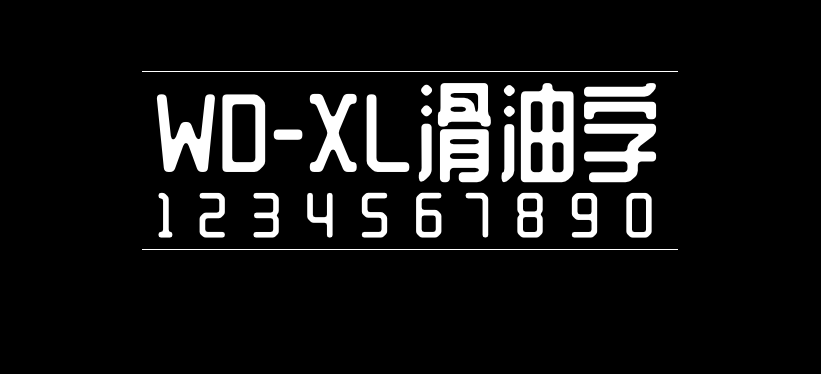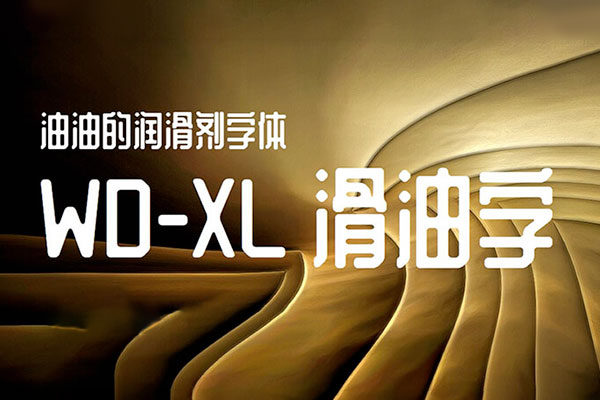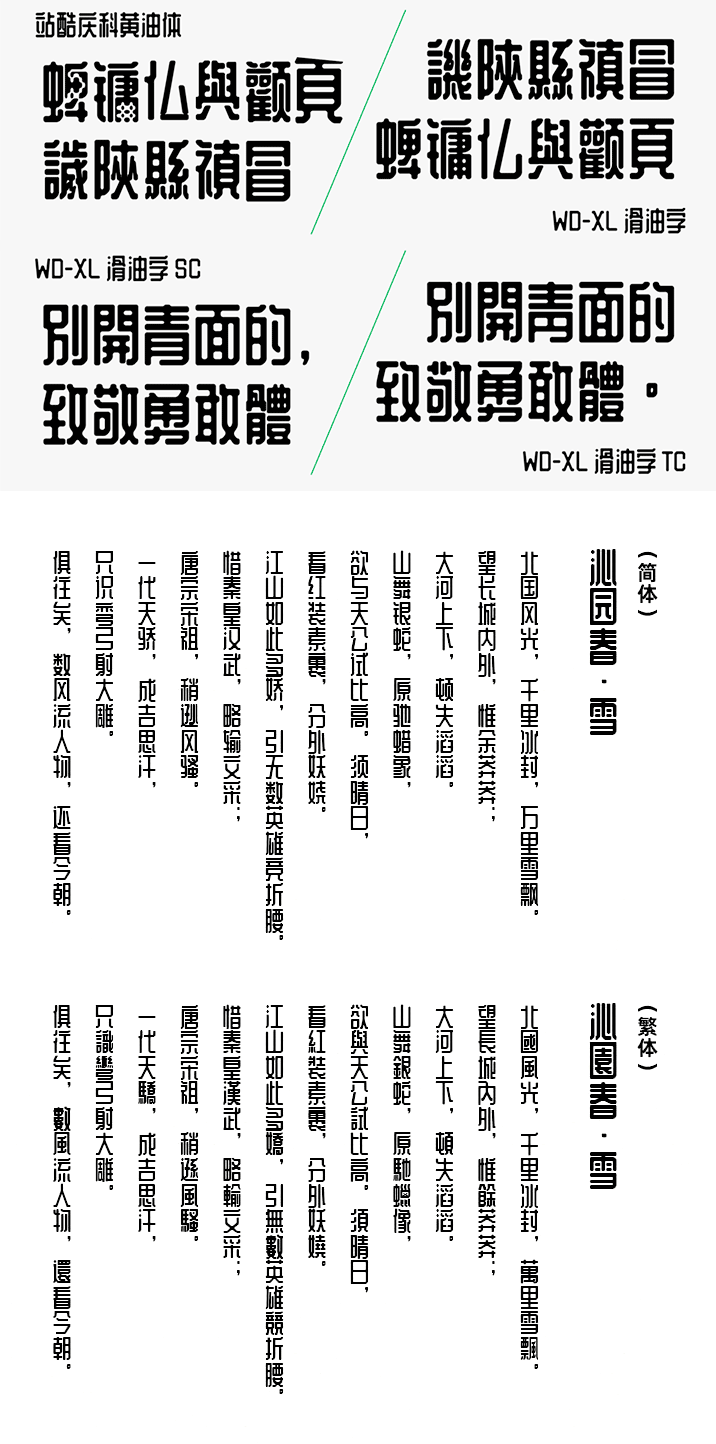
WD-XL滑油字
WD-XL滑油字的作者是来自马来西亚的夜煞之乐,在站酷庆科黄油体的基础上为繁体(正体)中文进行补字扩充,让其能够适配繁体(正体)中文环境,并且也补全标准中文字体所需的标点符号和功能。此外WD-XL滑油字还修正了站酷庆科黄油体一些存在的BUG,并对部分字形进行了优化。
WD-XL滑油字包含两个版本,一个是TC繁体中文版,字形符合港台书写习惯;另一个是SC简体中文版,字形符合中国大陆的书写习惯。两个版本字符都很全,简体繁体基本都不存在缺字现象。由于该字体主要是增补了繁体文字,所以自由君将该字体归类为繁体,事实上WD-XL滑油字的简体文字和繁体文字都是支持的而且字符都很全的,目前本站发布的版本是20201231版。